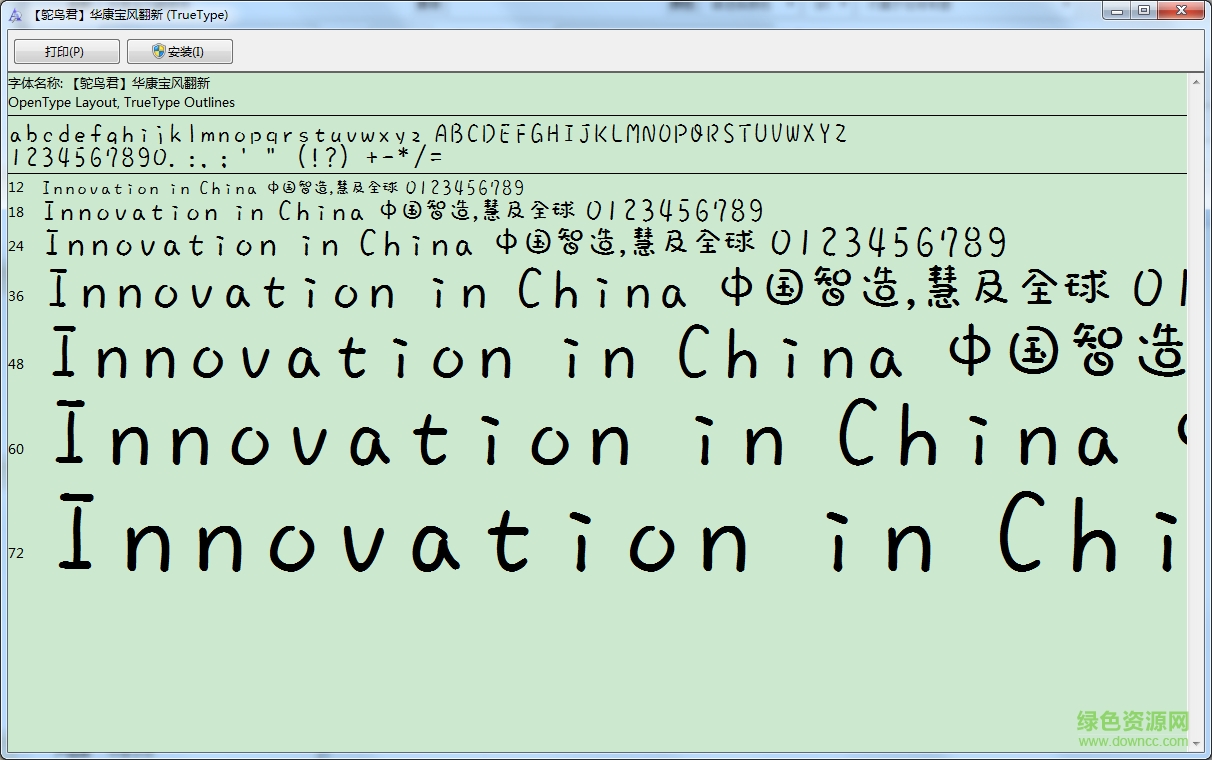
華康寶風(fēng)翻新體是一款非常美觀的簡(jiǎn)體字體,此款字體字型圓潤(rùn)清新,整體效果非常可愛,支持中文、英文、數(shù)字輸入轉(zhuǎn)換,廣泛的適用于平面設(shè)計(jì)、廣告設(shè)計(jì)、排版印刷等領(lǐng)域,喜歡的朋友歡迎來(lái)綠色資源網(wǎng)下載!
搜字網(wǎng)給大家提供一款華康寶風(fēng)翻新字體中文字體手機(jī)中文字體下載。這款手機(jī)字體是以華康寶風(fēng)字體為原形。華康寶風(fēng)體是一款帶有手寫風(fēng)格的兒童卡通字體,看上去非??蓯?,趣味實(shí)足。